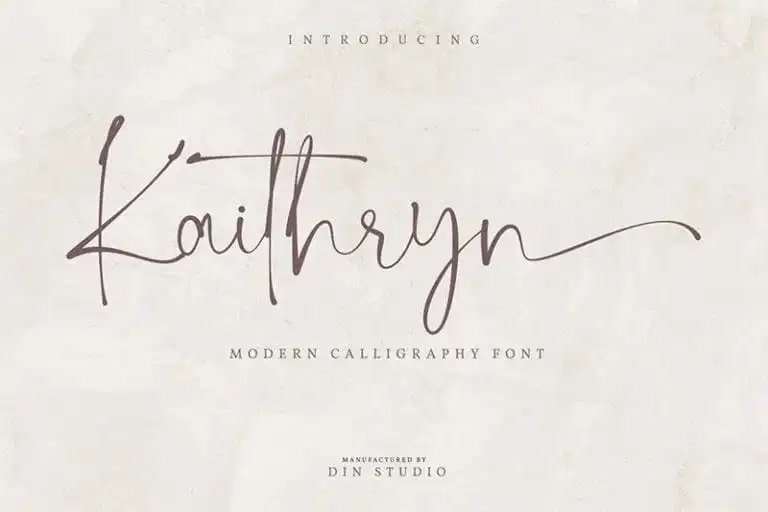
Kaithryn Script Font – Download Grátis
A Kaithryn Script Font é uma escolha perfeita para designers que valorizam a sofisticação dos desenhos manuais, mas querem obter a praticidade do uso digital. Introduzida por Din Studio na 99designs, essa fonte segue o estilo da escrita manual, com alternativas estilísticas e ligaturas que transformam a experiência de uso em uma verdadeira experiência visual realista. A Kaithryn Script é um tipo moderno baseado na calligrafia, tornando-a ideal para projetos profissionais em logotipos, marcas, casamentos e citações. Seja para criar os detalhes finos ou grandes texturas, a Kaithryn oferece uma experiência de escrita que vai além da tipografia convencional, trazendo um tipo belo e atrativo. Tornando-a uma escolha excepcional para qualquer projeto visual exigente.